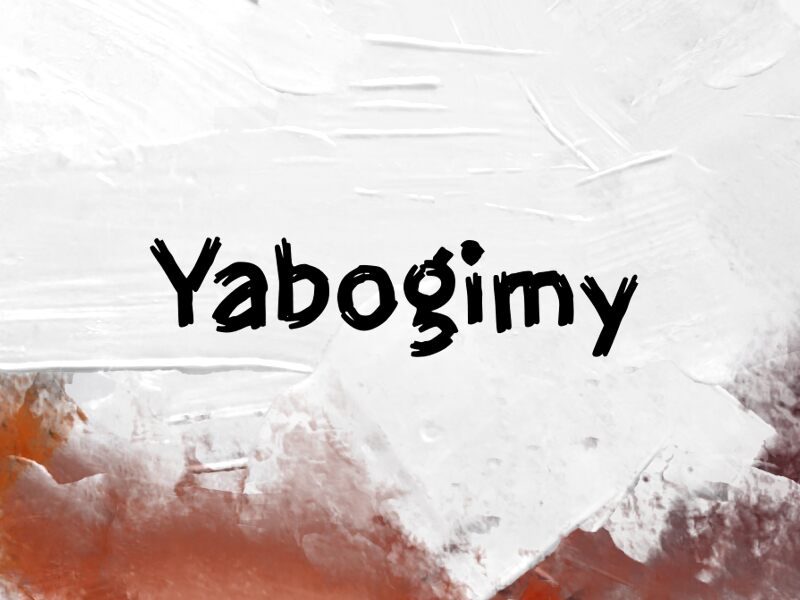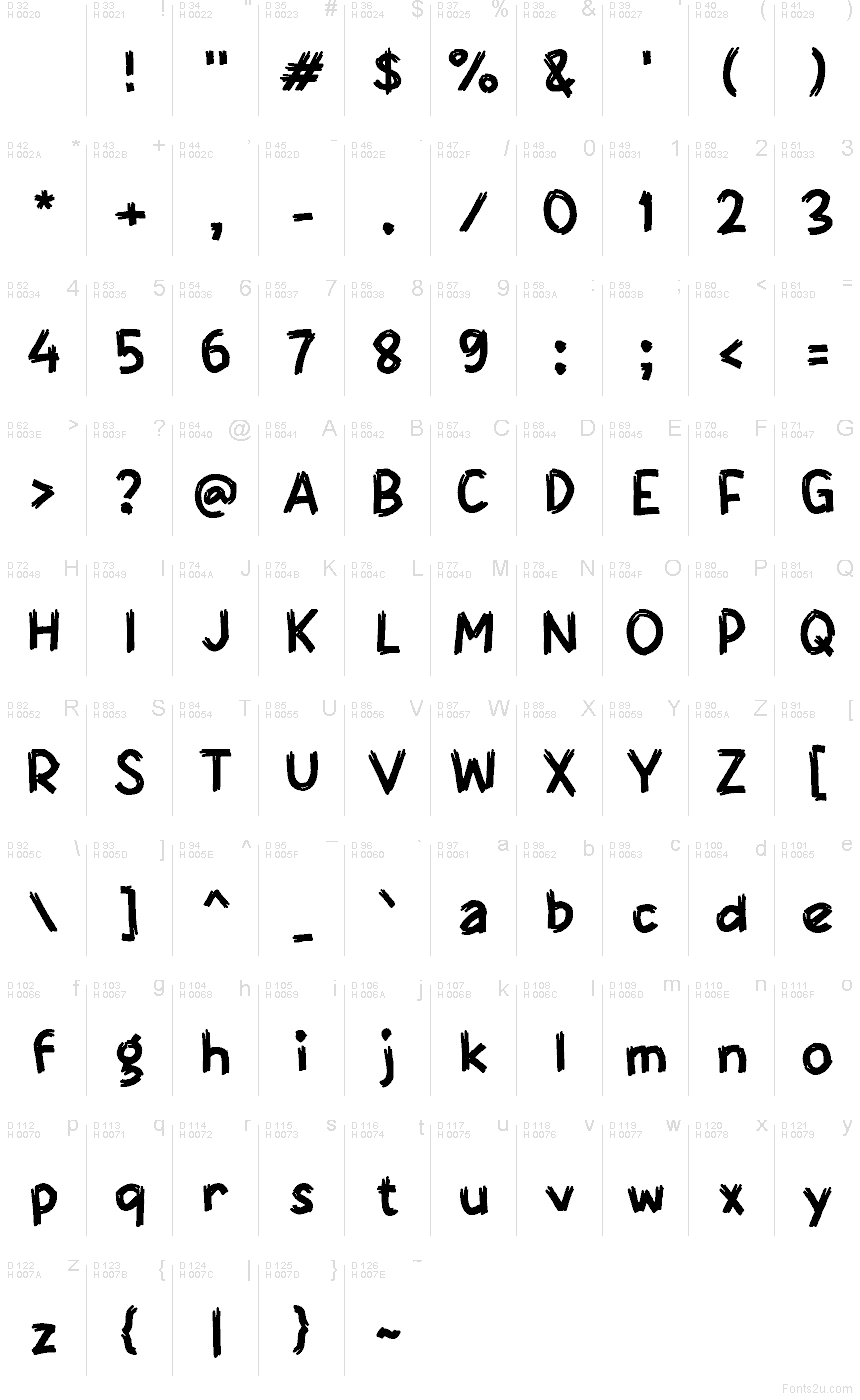
Yabogimy
Yabogimy от Wep — это бесплатный шрифт в стиле trash brush с дерзким, рукописным характером. Буквы выглядят так, будто их набросали толстым маркером: неровные края, резкие соединения и мелкие штрихи создают свободный ритм, далекий от идеальной аккуратности.
Отлично подходит для постеров, обложек альбомов, зинов, хоррор-заголовков, стритвир-графики и быстрых титров, где грубый штрих — часть месседжа. Будучи бесплатным шрифтом, Yabogimy также хорош для оформления обложек, коротких брендинговых акцентов и постов в соцсетях, которым нужно что-то живое и «грязное» вместо вылизанной типографики.